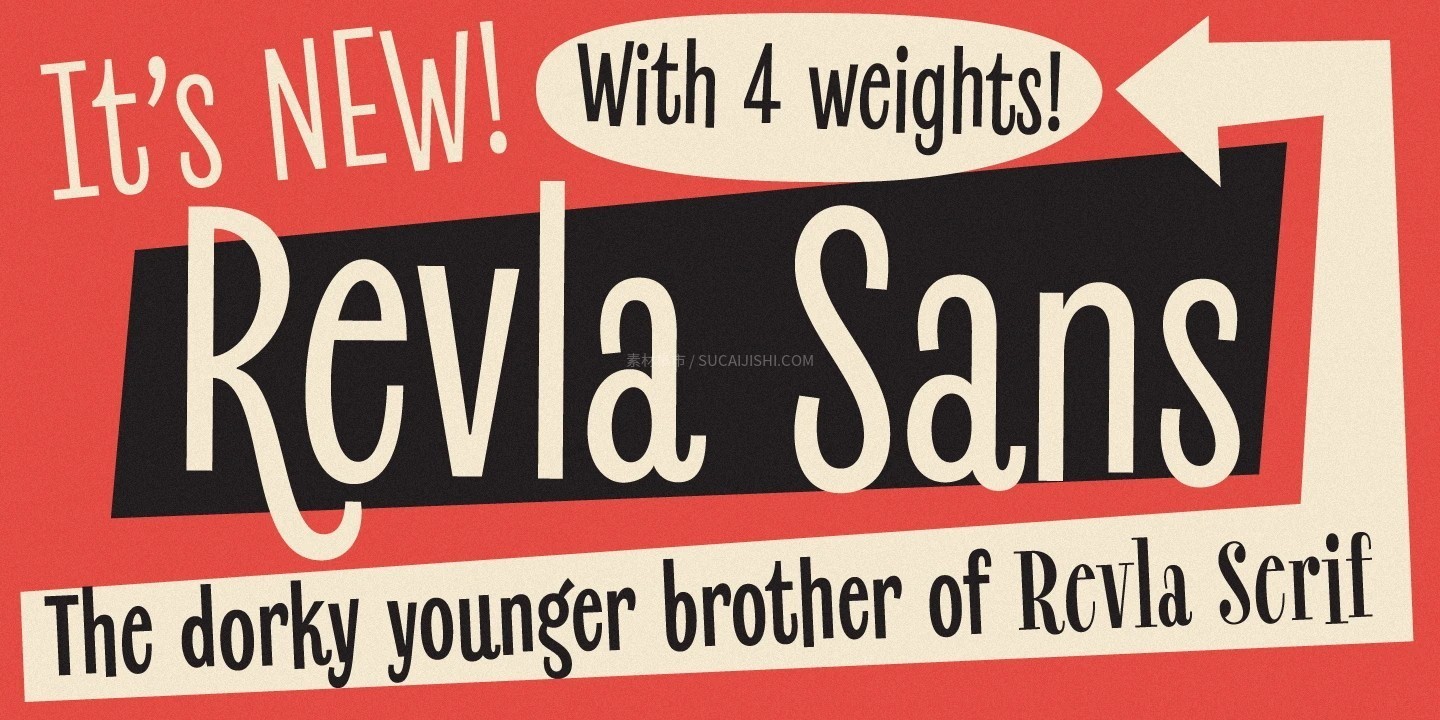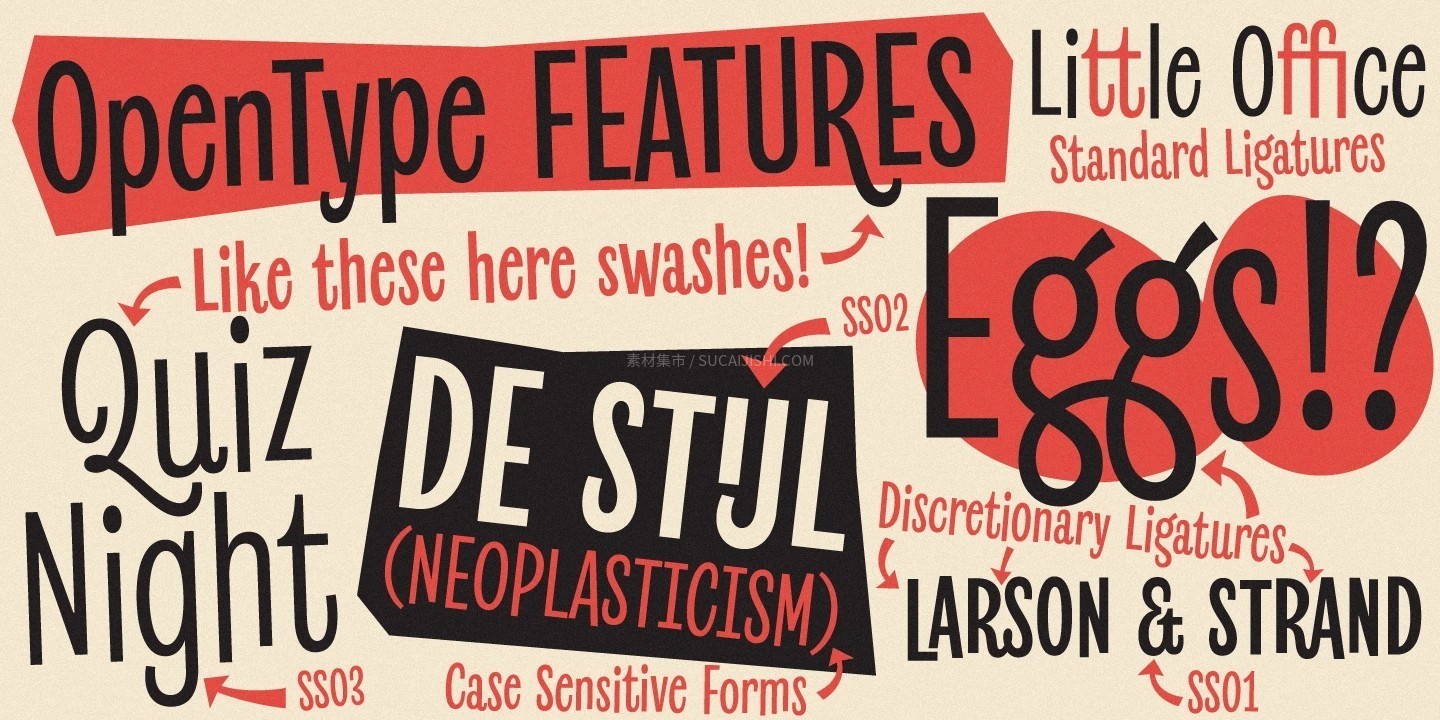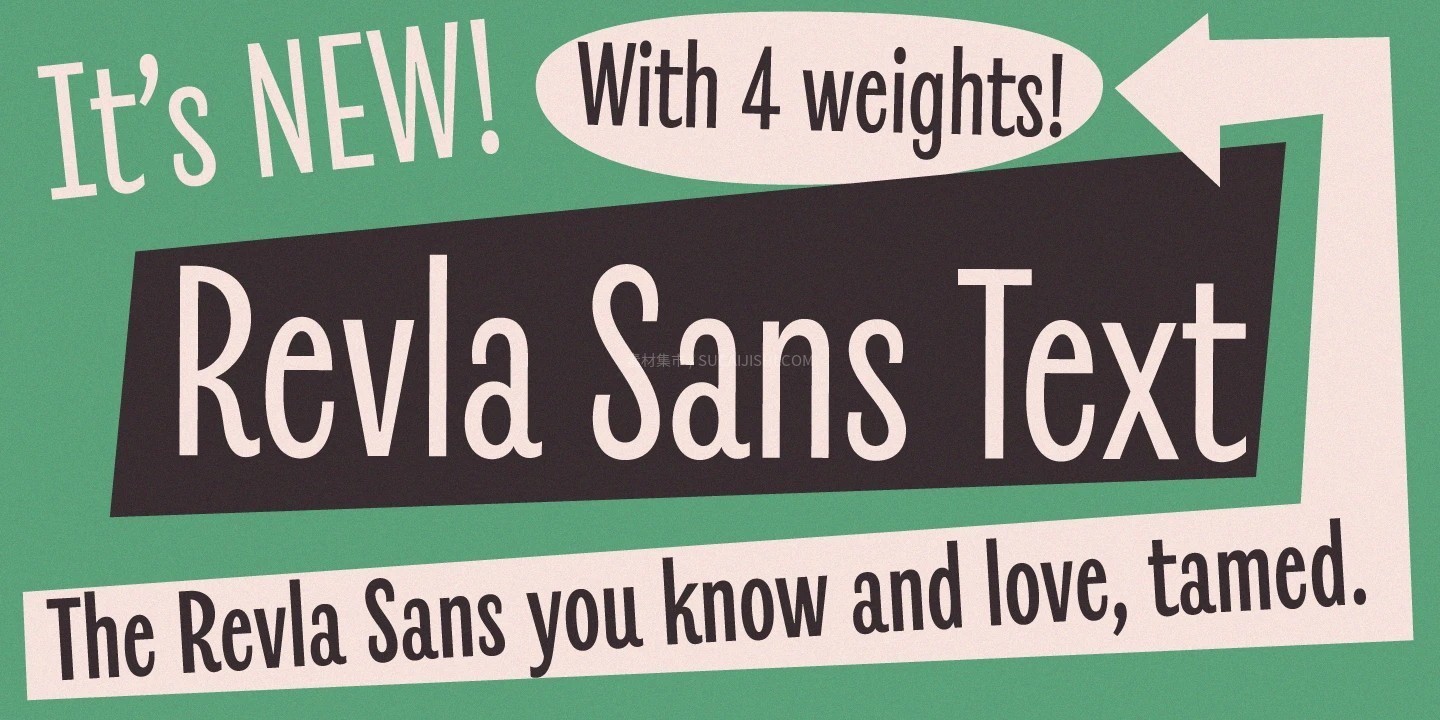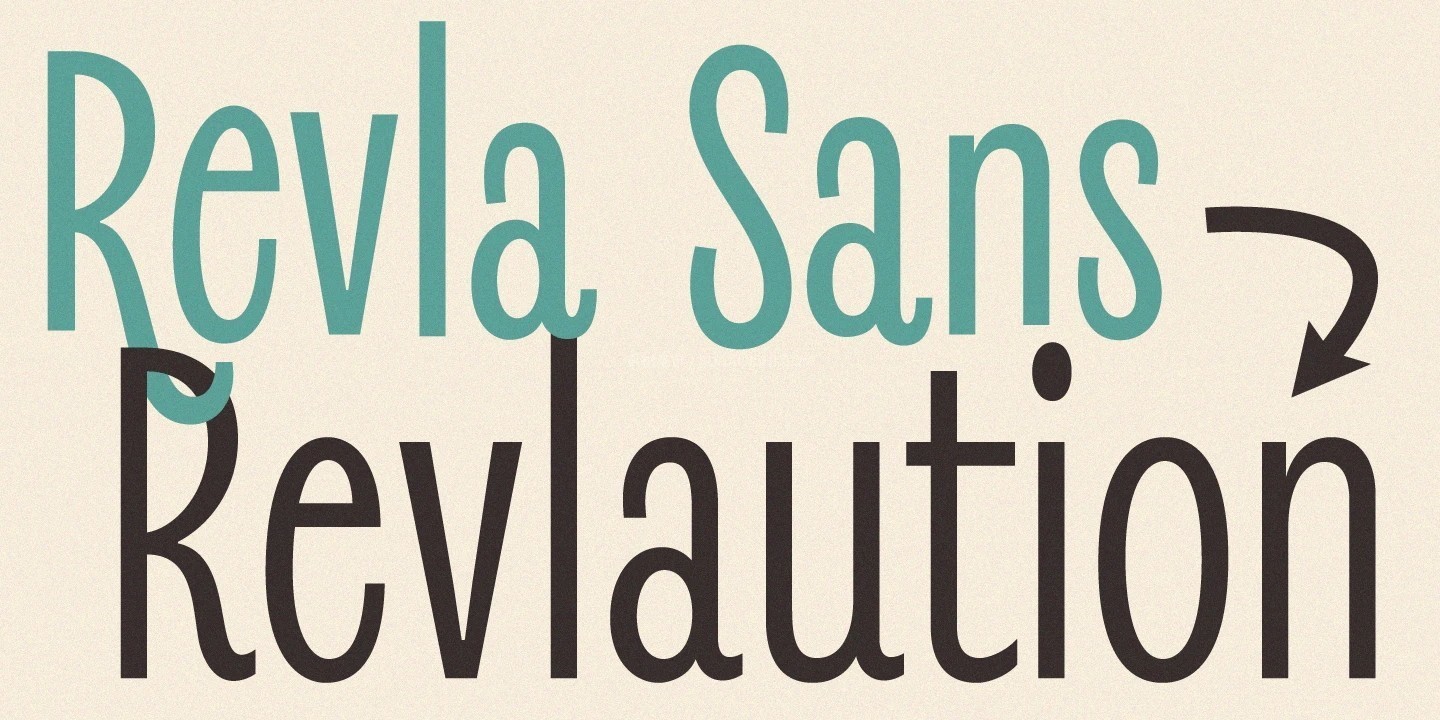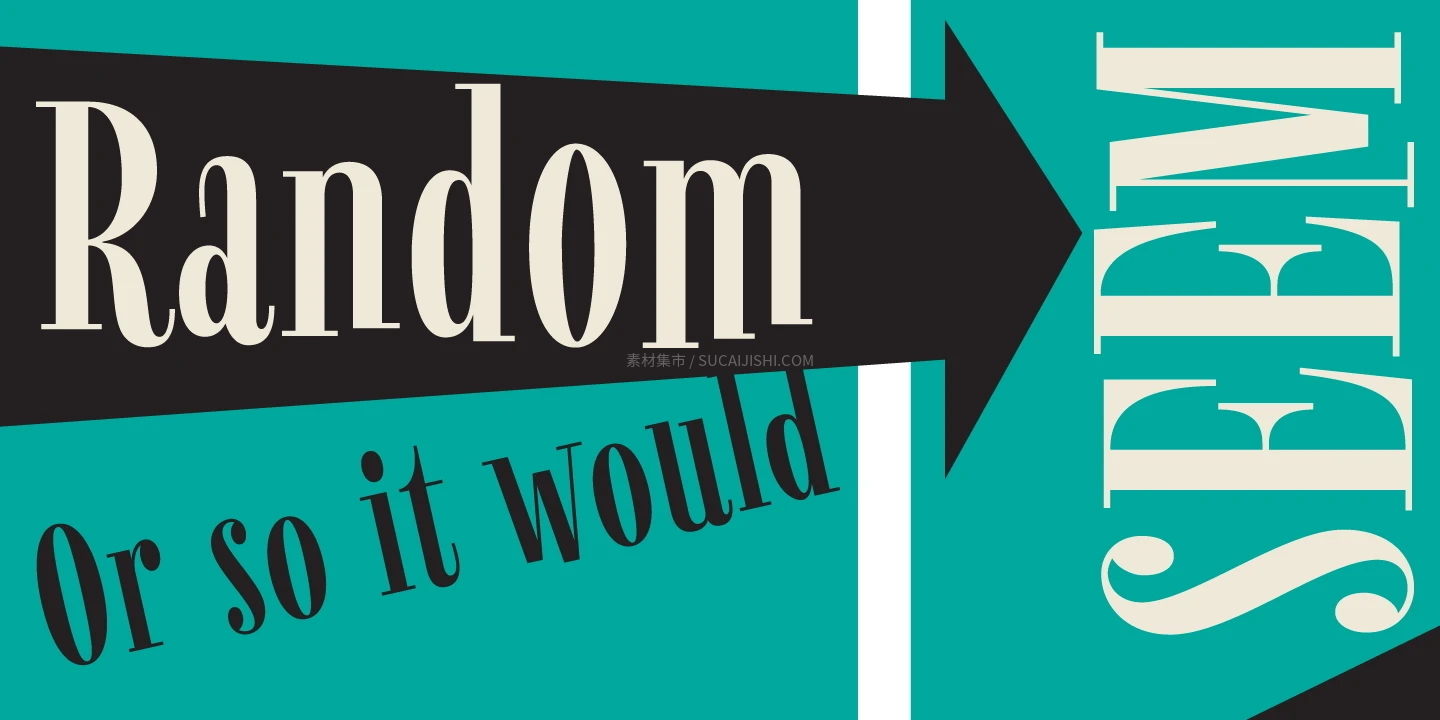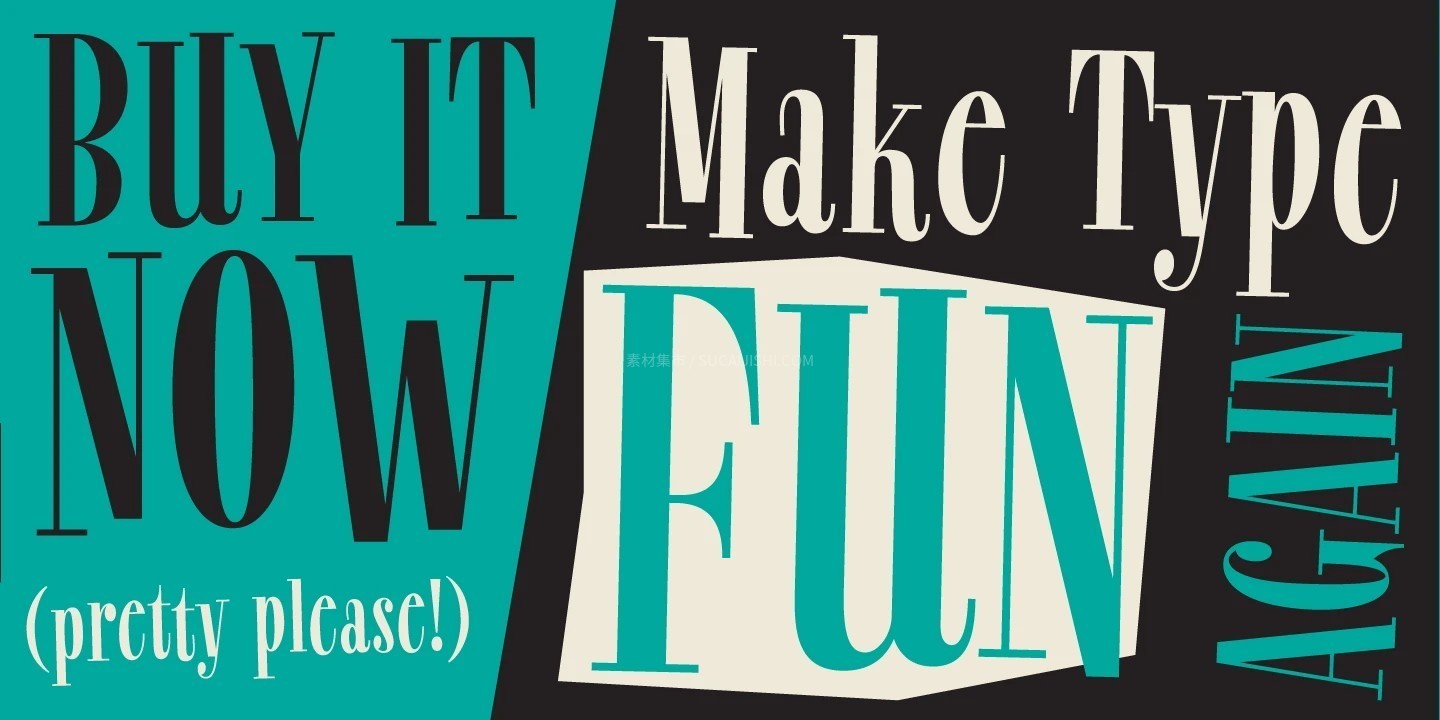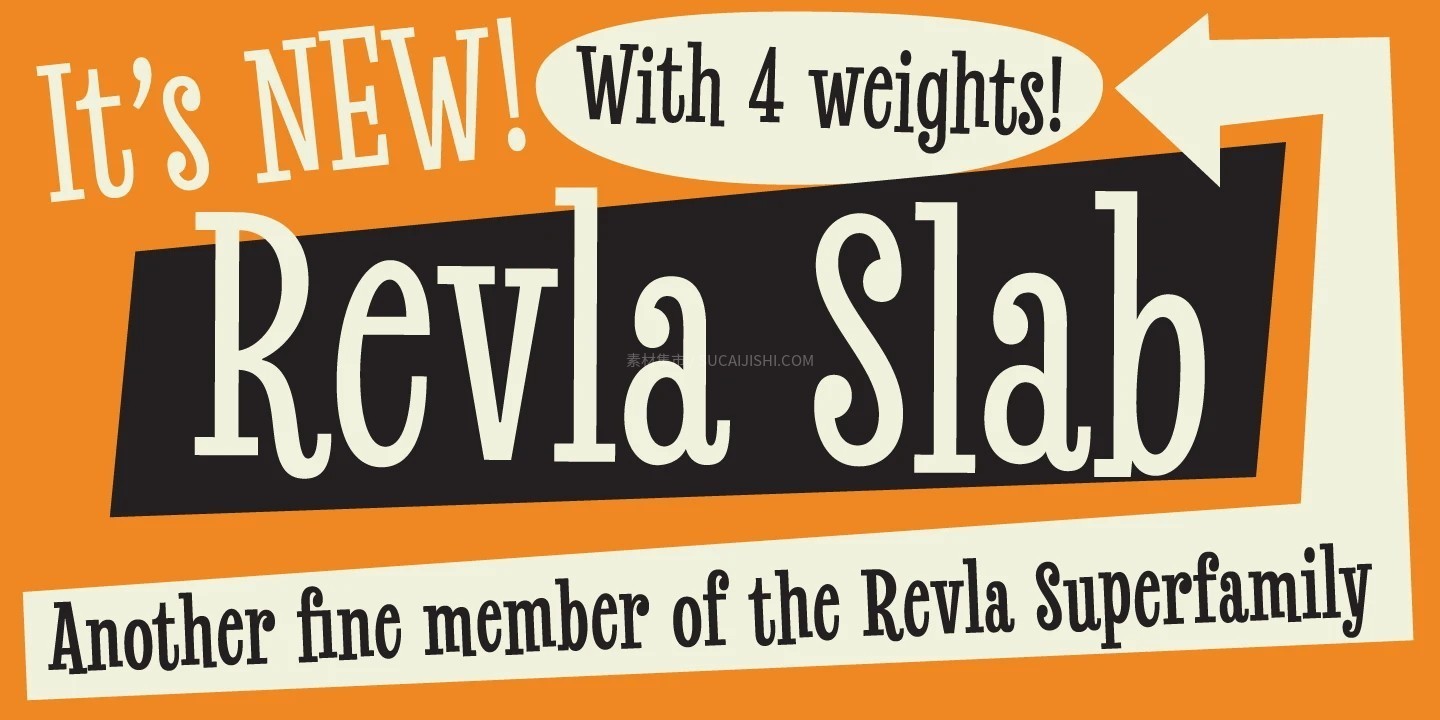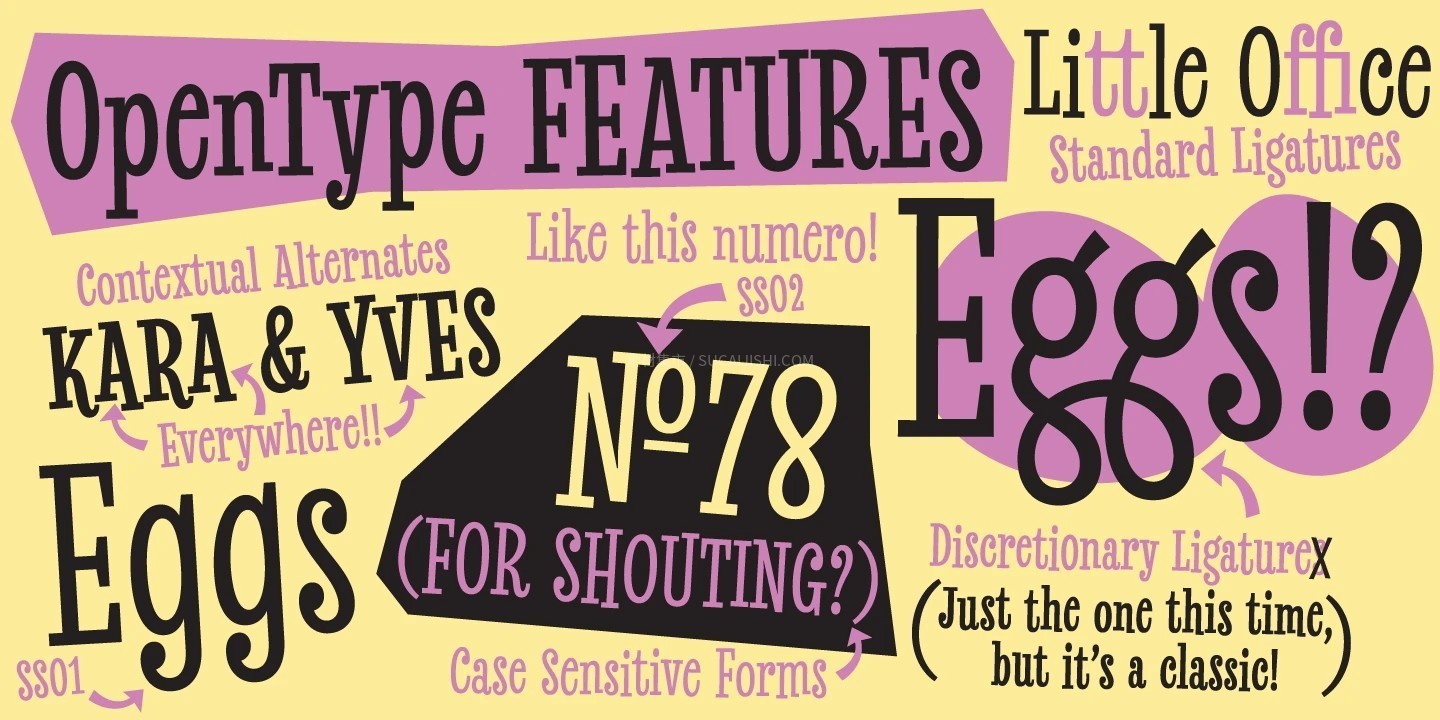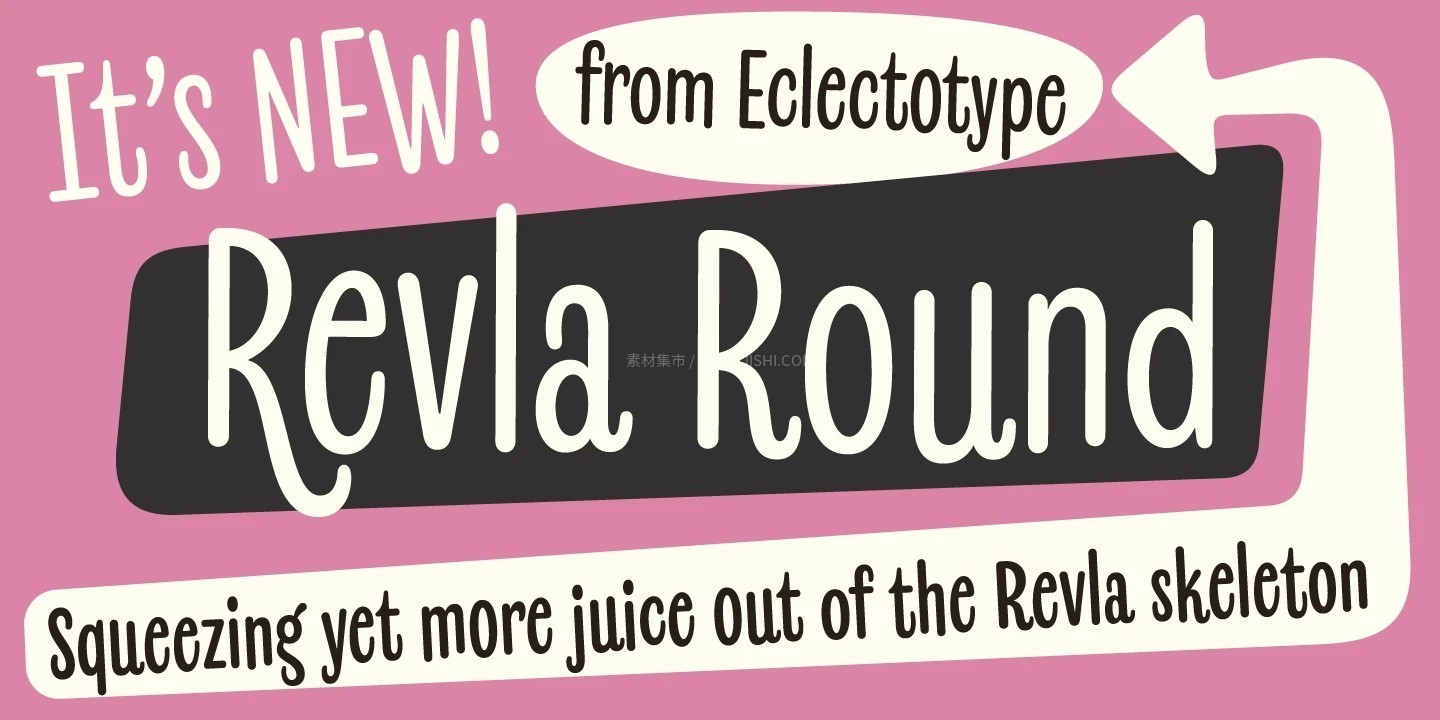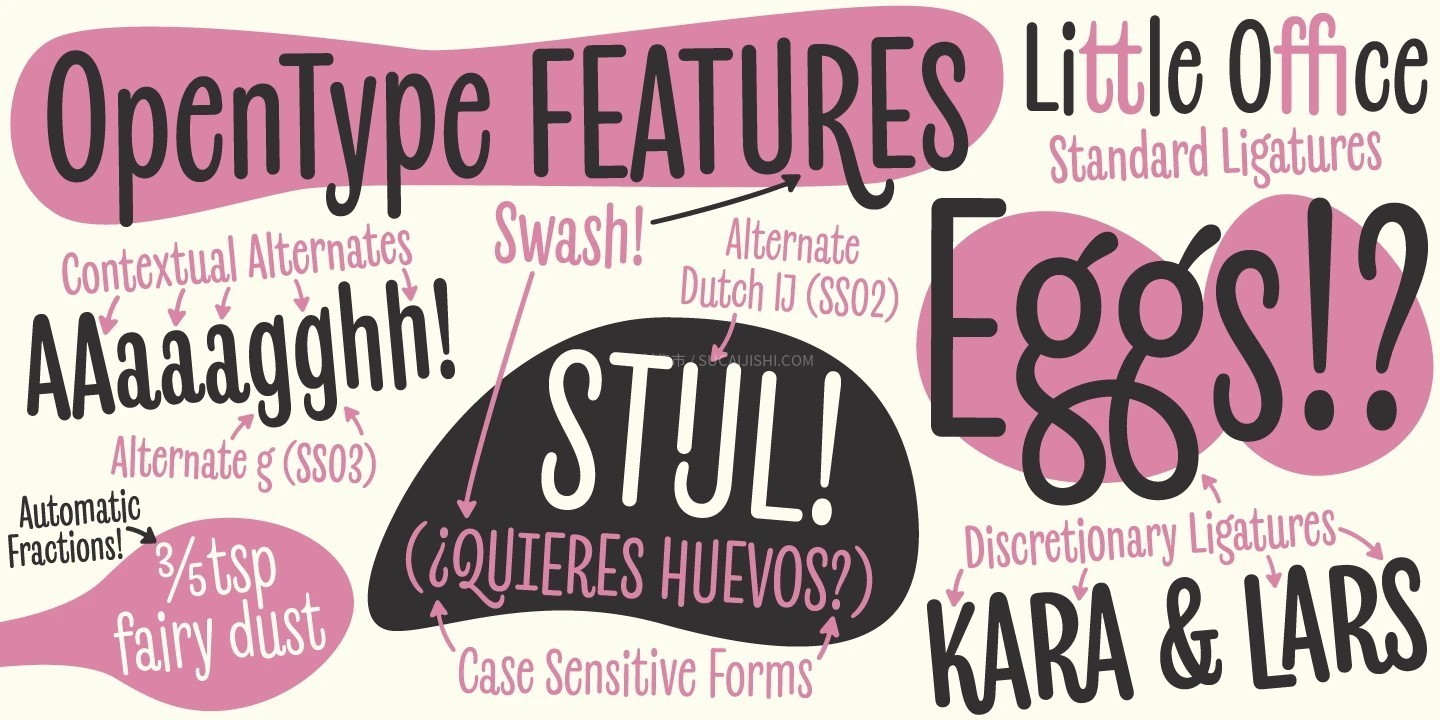
Revla 趣味复古全家族多风格英文字体
Revla 字体家族包含 17 款样式,涵盖圆体(Round)、无衬线(Sans)、文本无衬线(Sans Text)、衬线(Serif)及粗衬线(Slab)五大分类。结构统一且兼具独特趣味个性,既能独立承担标题视觉重心,也可多款式灵活混搭,帮助你打造出富有创意表现力与排版质感的专业设计作品。
Revla Round
Revla Sans
Revla Sans Text
Revla Serif
Revla Slab
Revla 字体家族包含 17 款样式,涵盖圆体(Round)、无衬线(Sans)、文本无衬线(Sans Text)、衬线(Serif)及粗衬线(Slab)五大分类。结构统一且兼具独特趣味个性,既能独立承担标题视觉重心,也可多款式灵活混搭,帮助你打造出富有创意表现力与排版质感的专业设计作品。